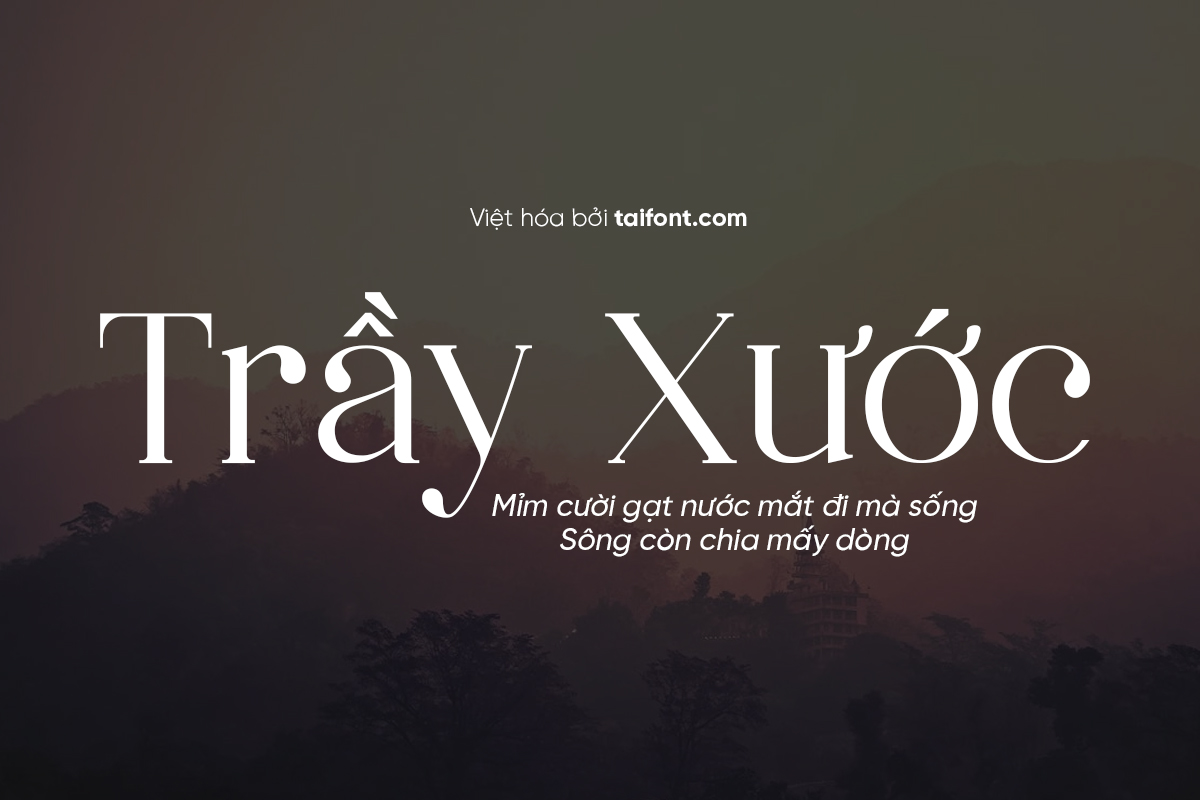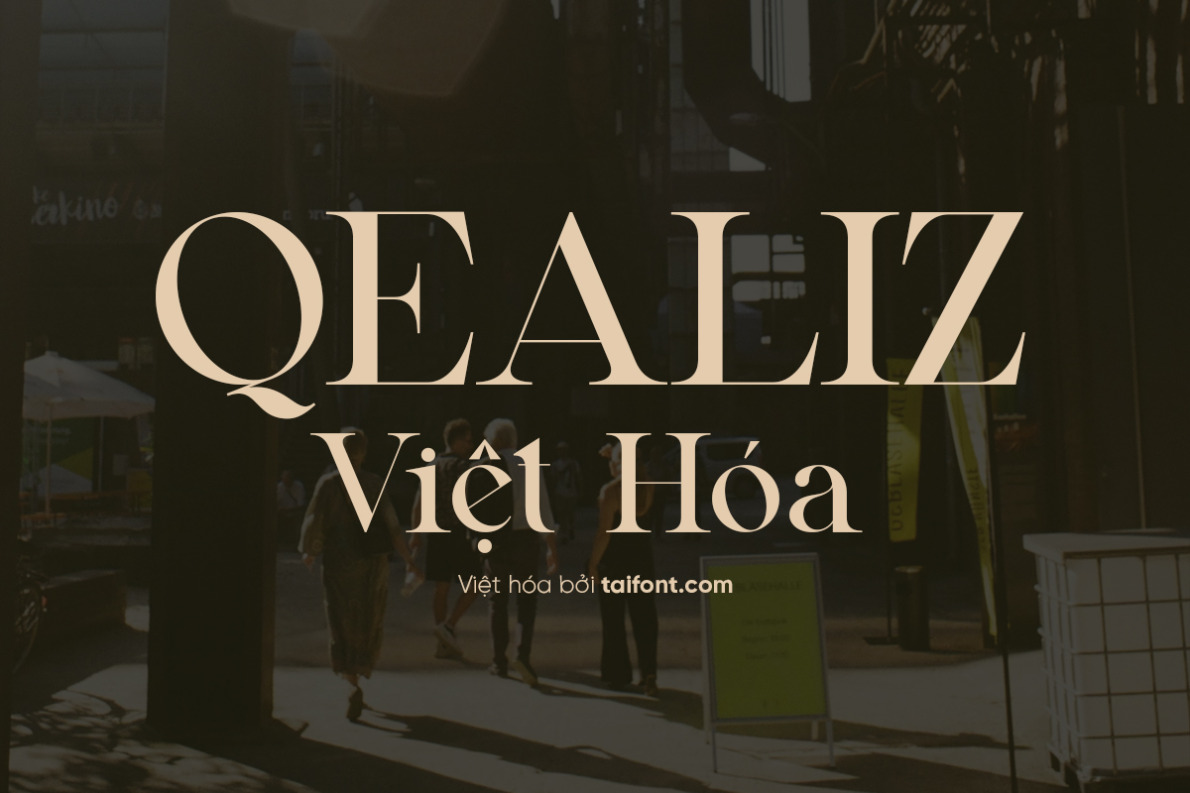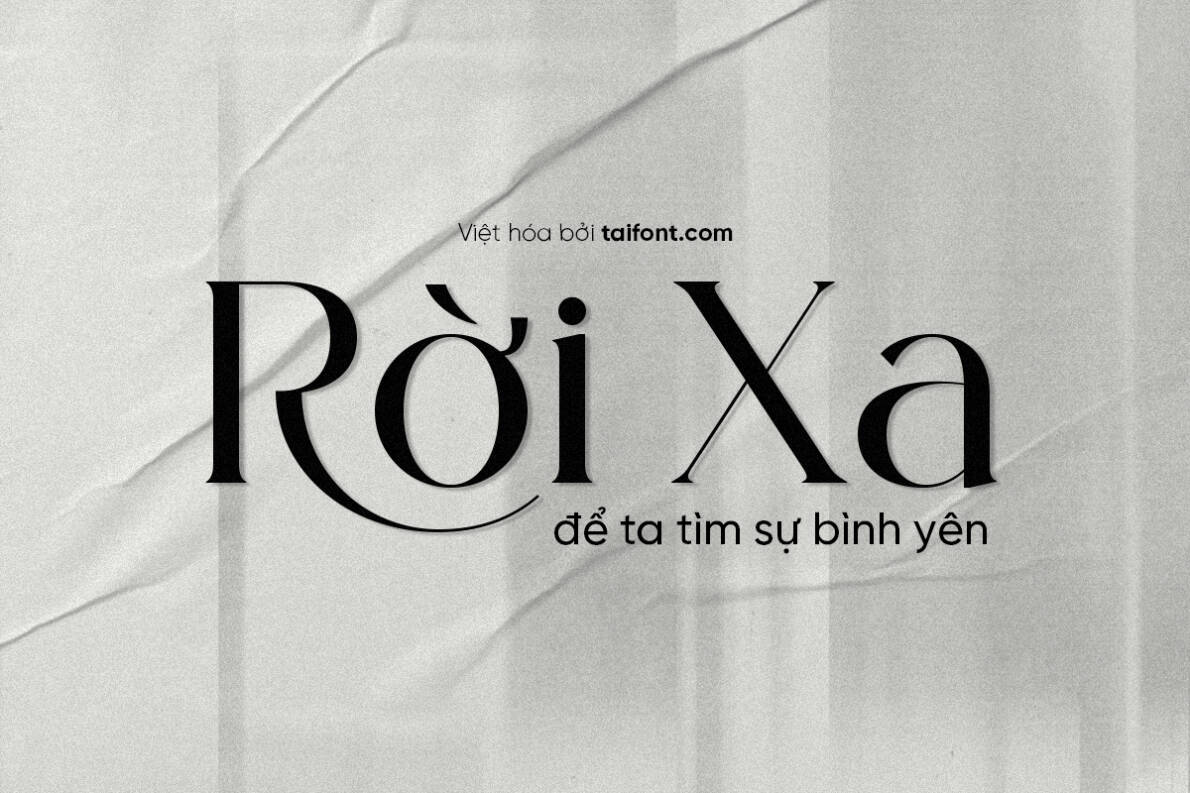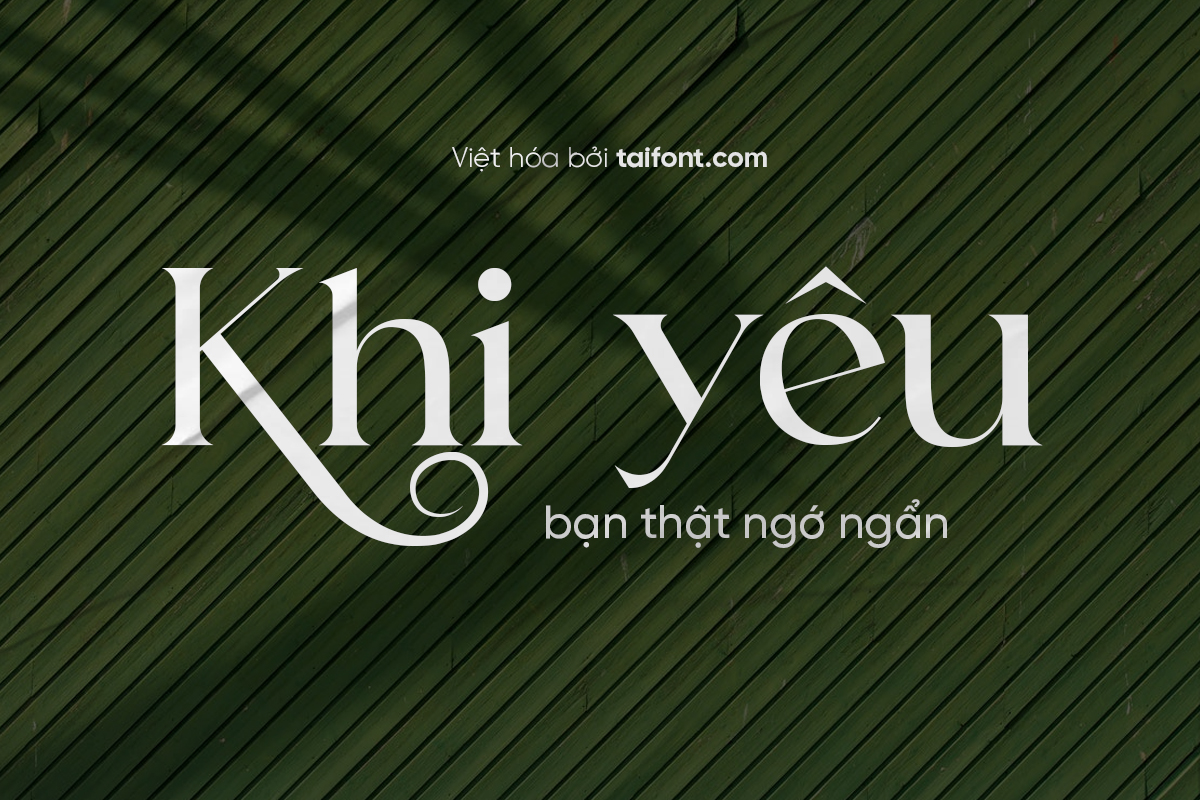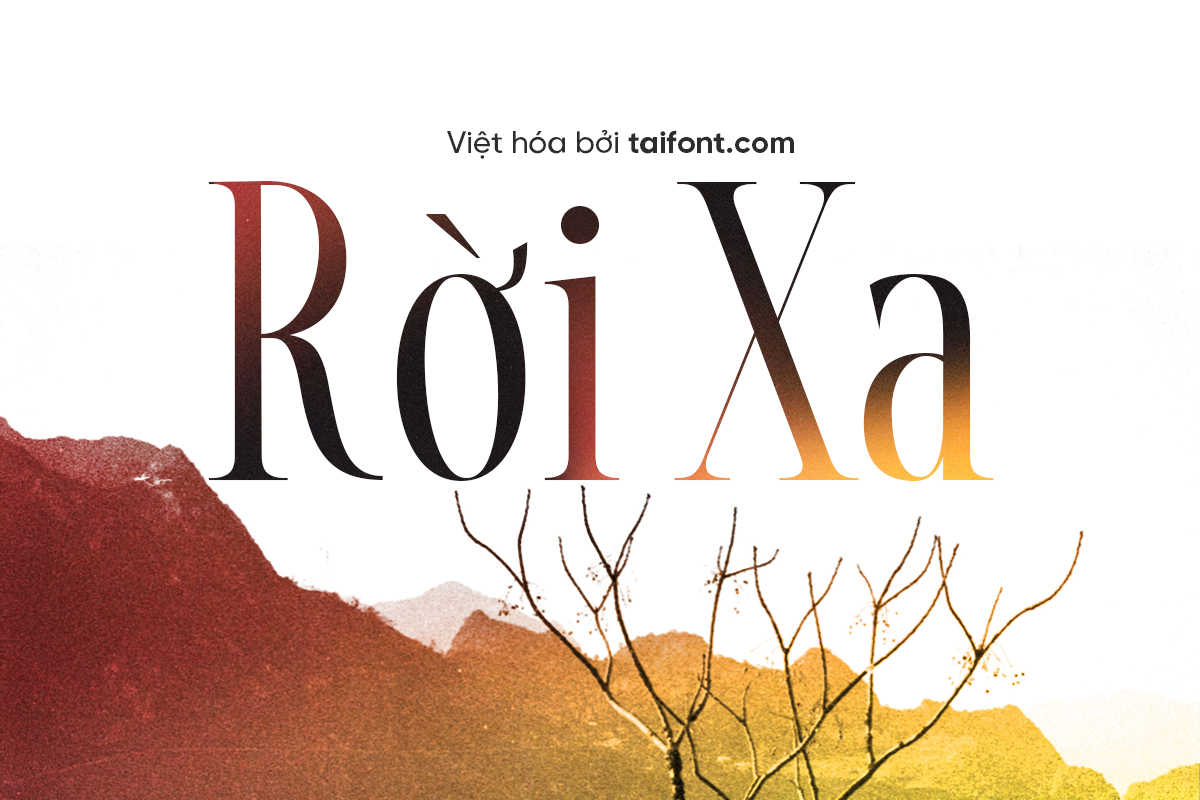
Top 5 font Việt hóa sang trọng luxury
Top 5 font Việt hóa sang trọng luxury, những font phù hợp với thiết kế thời trang quý phái, thẩm mỹ viện.
Top 1: Font Việt hóa TF Qealiz
Font Việt hóa TF Qealiz là một font chữ có chân toát lên vẻ sang trọng và thanh lịch. Nó thu hút sự chú ý và làm nổi bật mọi thiết kế. Nó hoàn hảo cho các thiết kế thiệp mời, logo công ty, tiêu đề phim, tên phim, danh thiếp, tiêu đề sách, tên thương hiệu và nhiều thiết kế khác.
Qealiz là một font chữ serif thanh lịch toát lên sự tinh tế và gắn kết. Các nét uốn lượn và nét ghép phong cách của nó làm cho nó trở thành lựa chọn hoàn hảo cho mọi dự án.
Top 2: Font Việt hóa TF Nortine
Top 3: Font Việt hóa TF
Top 4: Font Việt hóa TF
Top 5: Font Việt hóa TF Mallorga